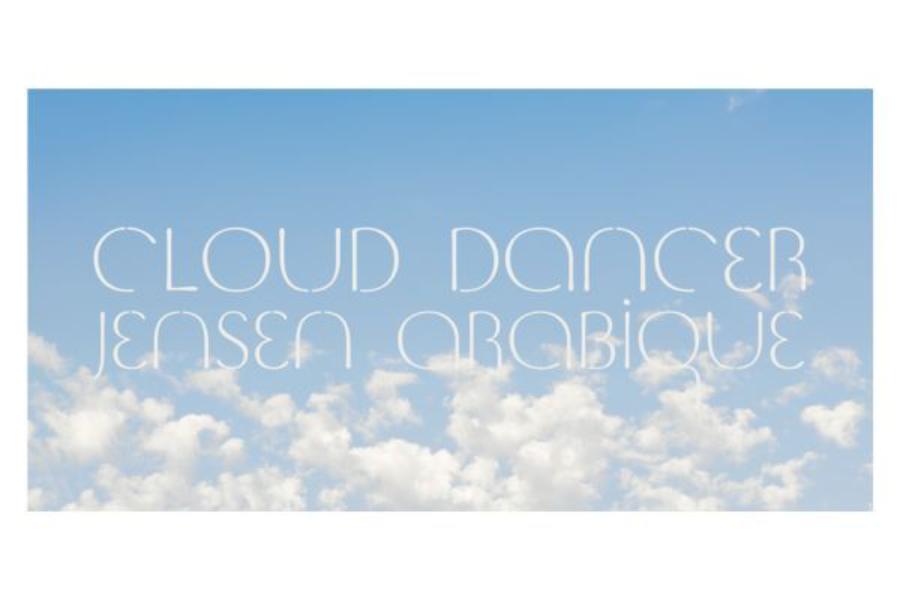
Monotype và PANTONE ra mắt font Cloud Dancer định hình xu hướng thiết kế 2026
Monotype hợp tác cùng PANTONE ra mắt font chữ Cloud Dancer lấy cảm hứng từ màu của năm 2026. Phân tích chi tiết xu hướng, ứng dụng và tác động đến ngành thiết kế.
Monotype và PANTONE ra mắt font Cloud Dancer định hình xu hướng thiết kế 2026
Năm 2026 chứng kiến một bước tiến mang tính biểu tượng trong ngành sáng tạo khi Monotype và PANTONE chính thức kết hợp để giới thiệu font chữ Cloud Dancer – bộ typography được phát triển dựa trên màu sắc của năm. Đây không chỉ là một sản phẩm thiết kế, mà còn là minh chứng cho sự hội tụ giữa hai yếu tố cốt lõi trong mỹ thuật hiện đại: màu sắc và chữ viết. Sự kết hợp này mở ra hướng tiếp cận mới, nơi cảm xúc, trải nghiệm và bản sắc thương hiệu được thể hiện một cách đồng nhất và sâu sắc hơn.
1. Tổng quan về sự hợp tác giữa Monotype và PANTONE
Sự hợp tác giữa Monotype và PANTONE không đơn thuần là một dự án sáng tạo mà là kết quả của quá trình phát triển dài hạn trong ngành thiết kế. Monotype là đơn vị đứng sau hàng loạt font chữ nổi tiếng toàn cầu, trong khi PANTONE giữ vai trò định hướng màu sắc với hệ thống tiêu chuẩn được sử dụng rộng rãi.
Trong nhiều năm, hai yếu tố typography và màu sắc thường được xử lý riêng biệt. Designer sẽ chọn font chữ phù hợp, sau đó mới cân nhắc bảng màu. Tuy nhiên, xu hướng hiện đại đòi hỏi sự đồng bộ cao hơn, nơi mọi thành phần thiết kế phải cùng truyền tải một thông điệp nhất quán.
Cloud Dancer chính là bước tiến trong tư duy này. Thay vì thiết kế chữ trước rồi áp màu, đội ngũ sáng tạo đã đi theo hướng ngược lại: bắt đầu từ cảm xúc mà màu sắc mang lại, sau đó chuyển hóa thành hình dạng chữ. Điều này tạo nên một hệ thống thiết kế liền mạch, nơi mỗi ký tự đều phản ánh tinh thần của màu sắc chủ đạo.
2. Cloud Dancer – Màu sắc định hình typography
Cloud Dancer không chỉ là một tên gọi, mà còn là biểu tượng của sự tinh tế và sáng tạo trong thiết kế. Màu sắc này mang lại cảm giác thanh lịch, nhẹ nhàng và đầy cảm hứng, góp phần định hình phong cách typography một cách độc đáo. Sự kết hợp hài hòa giữa màu sắc và chữ viết không chỉ tạo nên tính thẩm mỹ cao mà còn truyền tải thông điệp một cách hiệu quả, giúp nâng tầm giá trị của các sản phẩm thiết kế.
Ý nghĩa của màu Cloud Dancer
Cloud Dancer là gam màu mang sắc thái nhẹ nhàng, thanh thoát, gợi cảm giác cân bằng và yên bình. Trong bối cảnh xã hội hiện đại với nhiều áp lực, màu sắc này đại diện cho nhu cầu tìm kiếm sự thư giãn và ổn định về tinh thần.
Không quá nổi bật nhưng đủ tinh tế, Cloud Dancer tạo nên cảm giác “thở” trong thiết kế. Nó không áp đảo thị giác mà mang đến sự dễ chịu, giúp người dùng tập trung vào nội dung mà không bị phân tán.
Màu sắc này đặc biệt phù hợp với các thương hiệu hướng đến sự tối giản, hiện đại và thân thiện. Nó cũng phản ánh xu hướng thiết kế bền vững, nơi sự đơn giản và cân bằng được đặt lên hàng đầu.
Từ màu sắc đến hình dạng chữ
Quá trình chuyển đổi từ màu sắc sang typography là điểm đặc biệt nhất của Cloud Dancer. Các nhà thiết kế không chỉ nhìn vào màu sắc như một yếu tố thị giác, mà còn phân tích cảm xúc mà nó mang lại.
Từ đó, font chữ được xây dựng với các đường nét mềm mại, độ cong nhẹ và khoảng cách hợp lý. Các ký tự không quá sắc cạnh mà mang cảm giác “trôi”, giống như những đám mây di chuyển nhẹ nhàng trên bầu trời.
Tỷ lệ giữa các nét chữ cũng được điều chỉnh để tạo sự cân bằng. Không có chi tiết nào quá nổi bật, tất cả hòa quyện để tạo nên một tổng thể hài hòa. Đây chính là cách màu sắc ảnh hưởng trực tiếp đến cấu trúc typography.
3. Đặc điểm nổi bật của font Cloud Dancer
Font Cloud Dancer nổi bật với thiết kế tinh tế và hiện đại, mang lại cảm giác thanh lịch và mềm mại trong từng đường nét. Với sự kết hợp hài hòa giữa các yếu tố truyền thống và sáng tạo, font này phù hợp để sử dụng trong nhiều lĩnh vực như thiết kế đồ họa, in ấn và thương hiệu. Đặc biệt, Cloud Dancer sở hữu độ tương phản vừa phải, giúp tăng khả năng đọc và tạo điểm nhấn ấn tượng cho nội dung. Đây là lựa chọn lý tưởng dành cho những ai tìm kiếm một kiểu chữ vừa độc đáo vừa chuyên nghiệp.
Thiết kế tối giản nhưng tinh tế
Cloud Dancer theo đuổi phong cách tối giản, loại bỏ những chi tiết không cần thiết để tập trung vào trải nghiệm đọc. Tuy nhiên, sự đơn giản này không hề đơn điệu.
Mỗi ký tự đều được tinh chỉnh kỹ lưỡng, từ độ dày nét chữ đến khoảng cách giữa các chữ cái. Những chi tiết nhỏ như góc bo hay độ nghiêng đều góp phần tạo nên sự khác biệt.
Tính linh hoạt cao
Một trong những điểm mạnh của Cloud Dancer là khả năng thích ứng với nhiều ngữ cảnh khác nhau. Font có thể sử dụng trong tiêu đề lớn, nội dung dài, giao diện số hoặc in ấn mà vẫn giữ được tính nhất quán.
Điều này giúp designer tiết kiệm thời gian khi không cần thay đổi quá nhiều font trong cùng một dự án. Đồng thời, nó cũng giúp thương hiệu duy trì hình ảnh đồng bộ trên nhiều nền tảng.
Tối ưu cho môi trường số